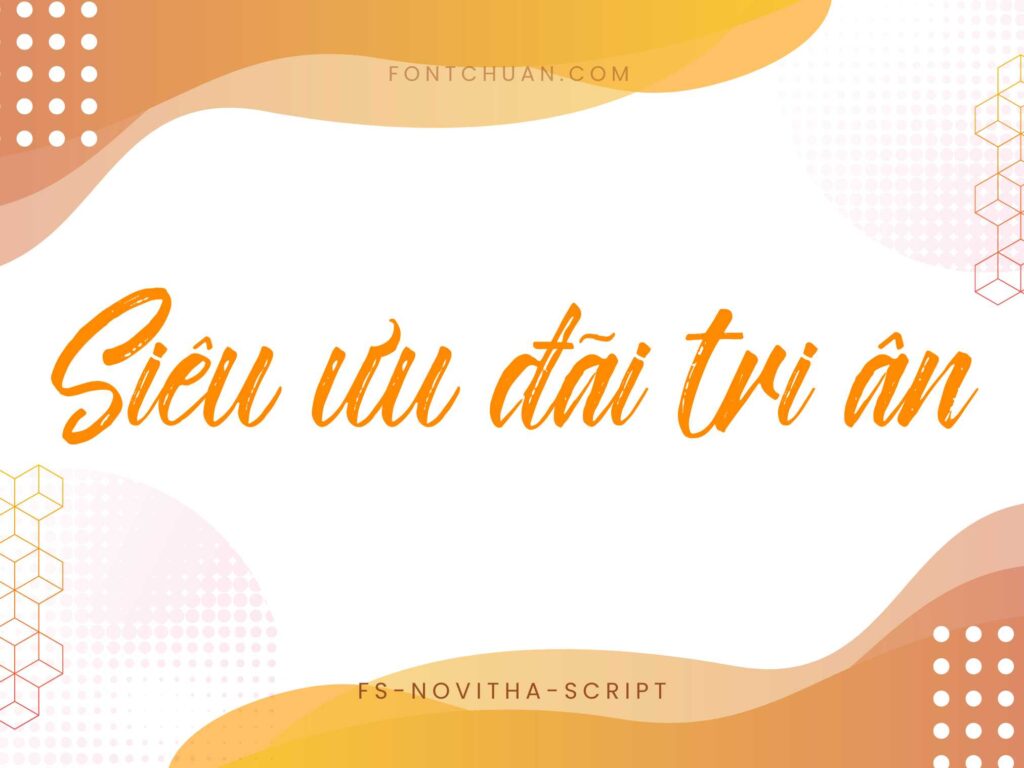
Font FS Novitha Script Việt Hóa
Novitha Script là một font chữ viết tay hiện đại, được thiết kế bởi Ryan Prasetya. Font này được phát triển bằng cách sử dụng bút lông, mang lại cảm giác mạnh mẽ và cá tính cho văn bản. Với sự Việt hóa của Phông Chữ Việt, Novitha Script hỗ trợ đầy đủ các ký tự tiếng Việt, giúp người dùng dễ dàng áp dụng trong các thiết kế đa ngôn ngữ. Thành viên của Font Chuẩn đã sưu tầm và chia sẻ font này nhằm đáp ứng nhu cầu của cộng đồng thiết kế.
Về đặc điểm thiết kế, Novitha Script bao gồm các ký tự cơ bản, chữ số, dấu câu và 99 ký tự thay thế cùng với ligature, hỗ trợ hơn 30 ngôn ngữ khác nhau. Font này đặc biệt phù hợp cho các dự án thiết kế như logotype, thiết kế áo thun, poster typography và thiết kế trích dẫn. Ngoài ra, Novitha Script cũng thích hợp cho các sự kiện như lễ hội, sinh nhật, Valentine và Trung thu, mang lại cảm giác ấm áp và gần gũi. Trong lĩnh vực ngành nghề, font này được ứng dụng rộng rãi trong quảng cáo, thiết kế thiệp cưới, giáo dục và công nghệ, góp phần tạo nên sự độc đáo và thu hút cho các sản phẩm và thương hiệu.